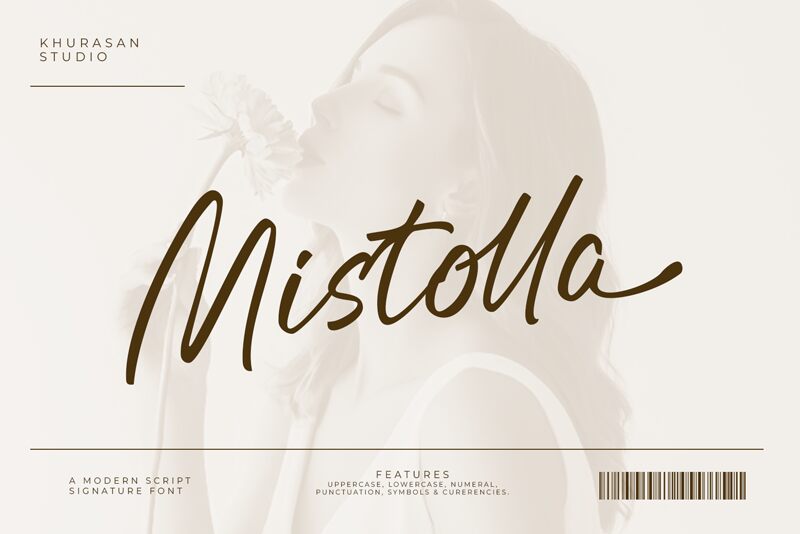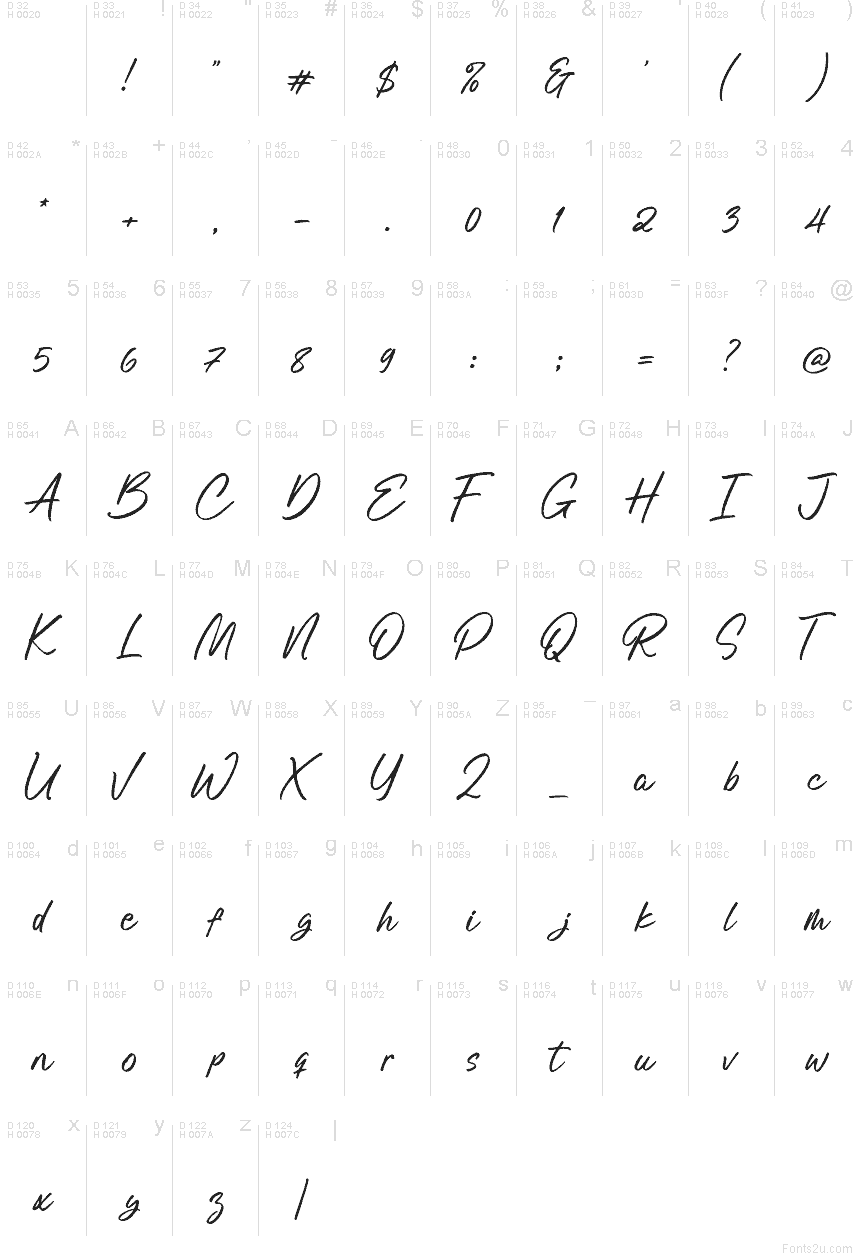
Mistolla je bezplatné ručne písané písmo od Khurasan, ktoré stavia na uvoľnenom štýle podpisu s vysokými začiatočnými ťahmi a rýchlym, prepojeným pohybom. Písmená pôsobia vzdušne a neformálne, s jemnou linkou pripomínajúcou fixku a niekoľkými ľahkými ozdobami, ktoré zachovávajú osobitý rytmus namiesto príliš vylešteného vzhľadu.
Hodí sa na branding, obaly, príspevky na sociálne siete, jedálne lístky v kaviarňach a nadpisy všade tam, kde by bezplatné písmo malo pôsobiť ľudsky, a nie strojene. Použite ho na krátke titulky, návrhy log alebo texty zamerané na názvy, pretože rozmáchlé začiatky a plynulé spojenia dodávajú aj krátkemu slovu pocit, akoby bolo napísané jedným ťahom.